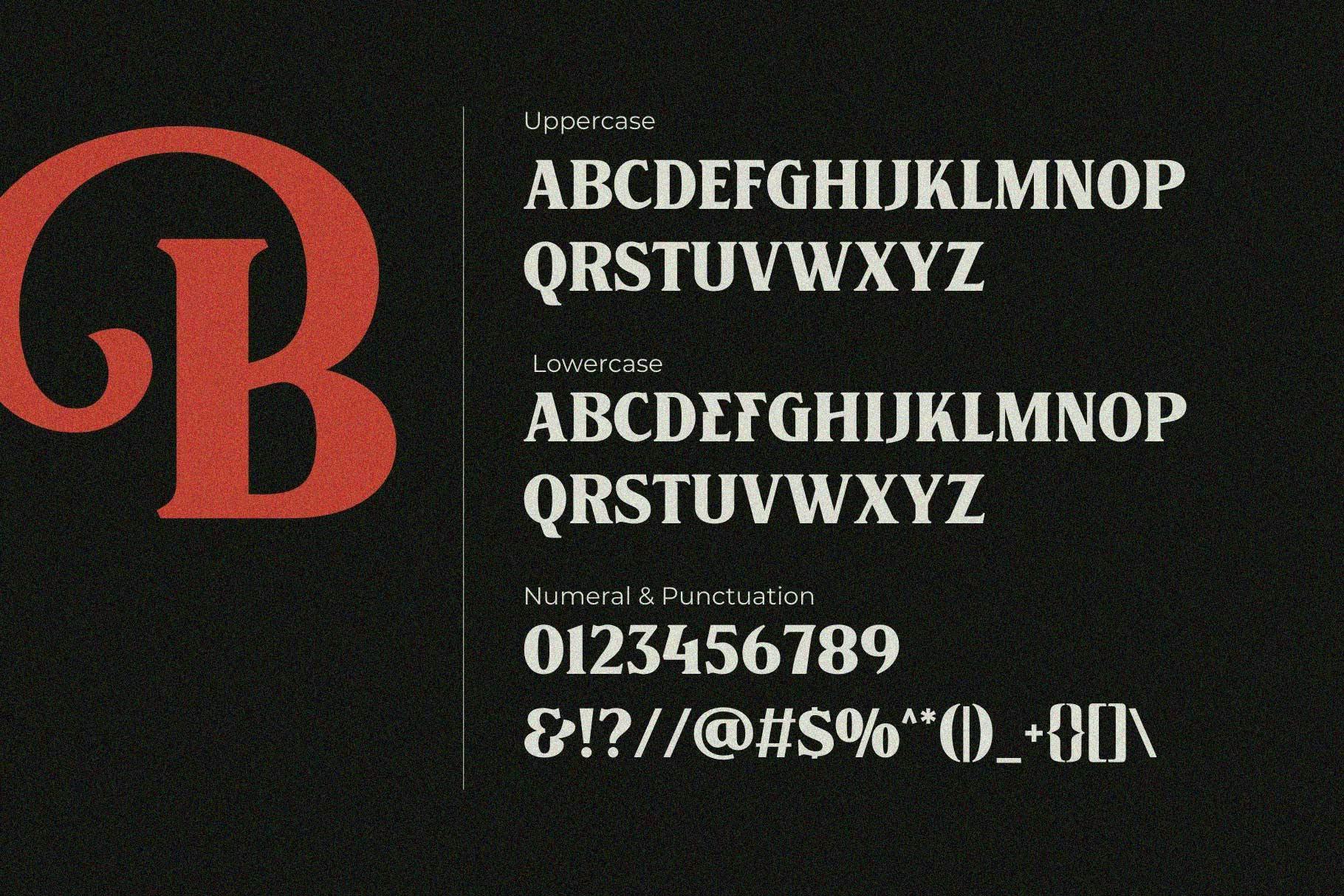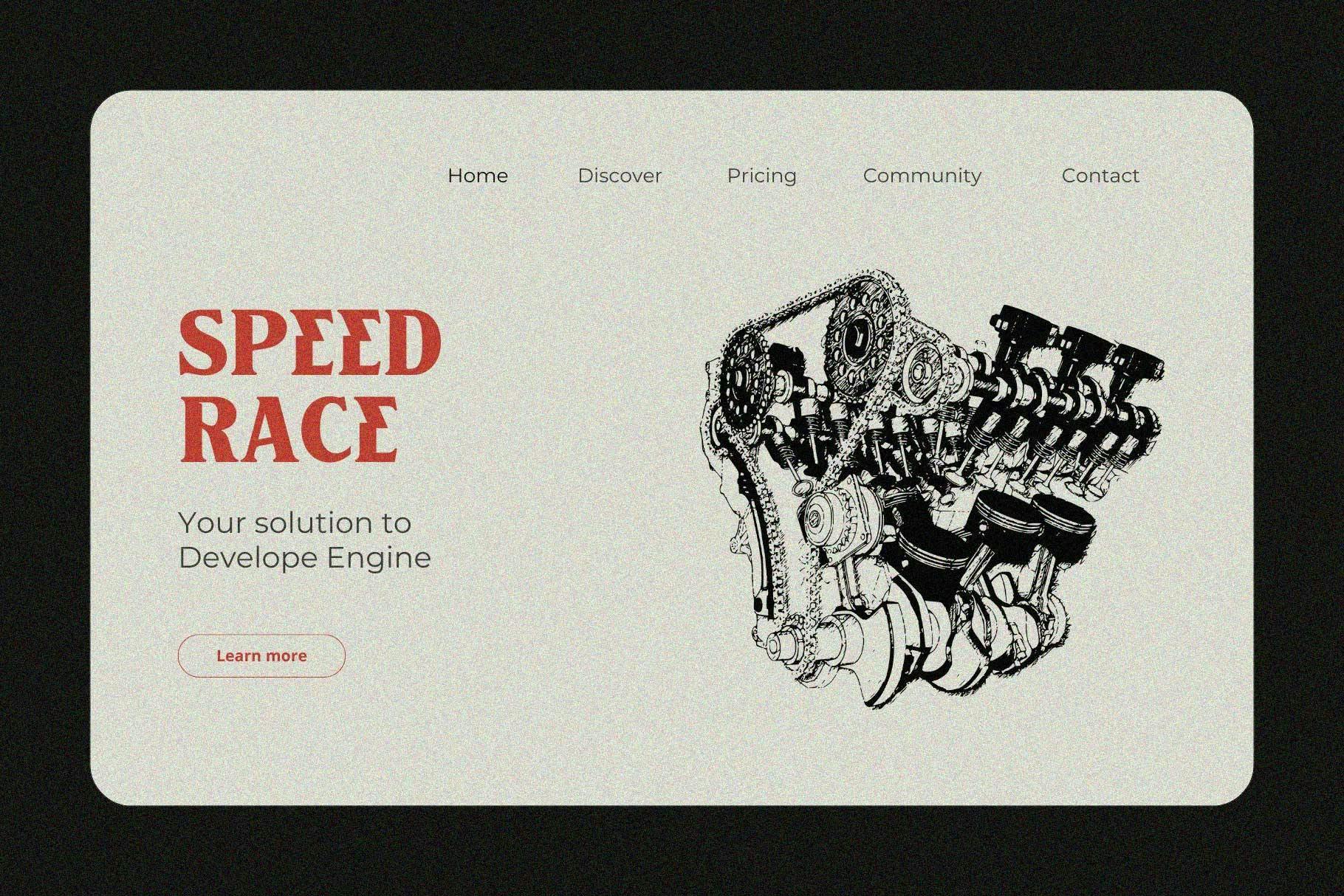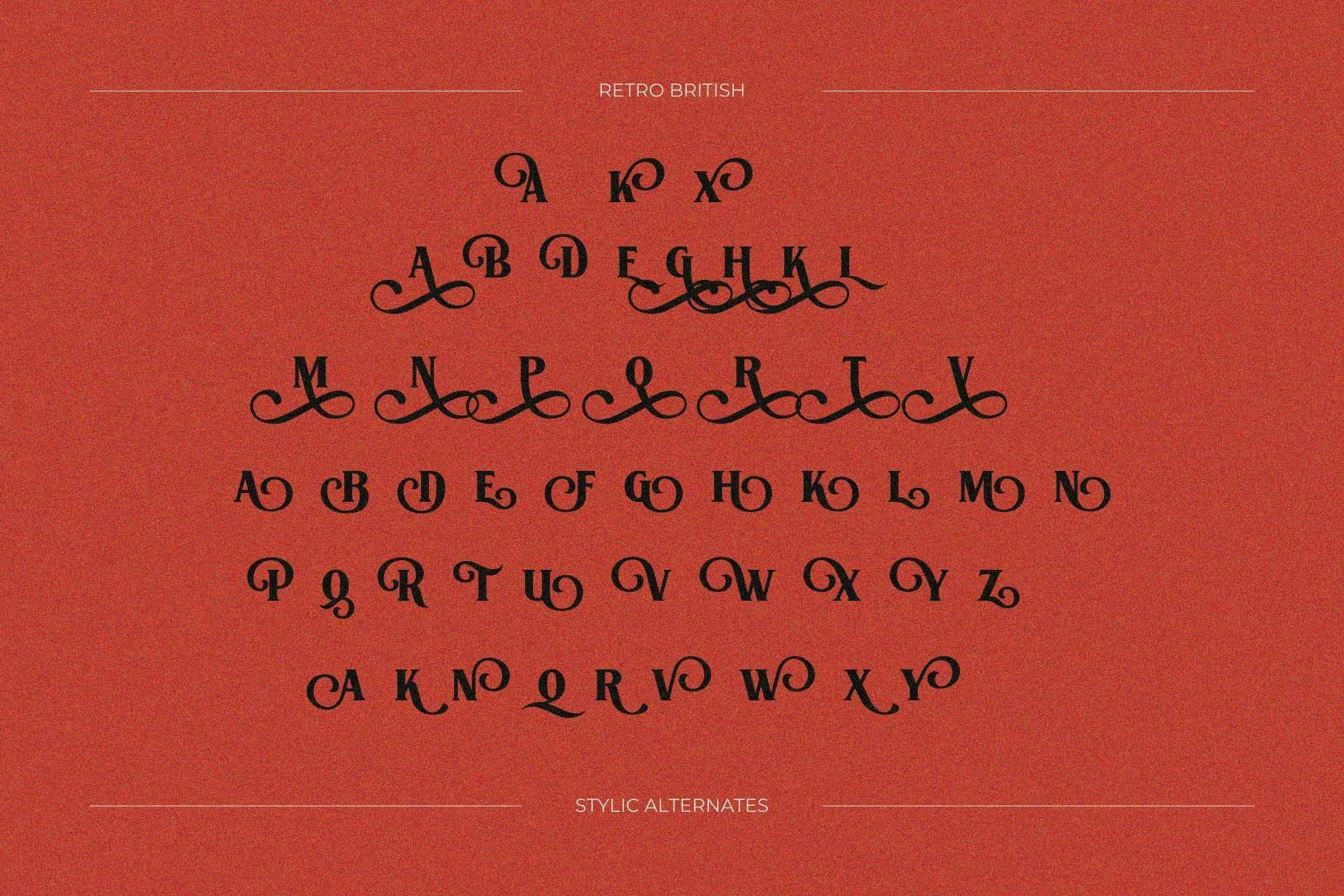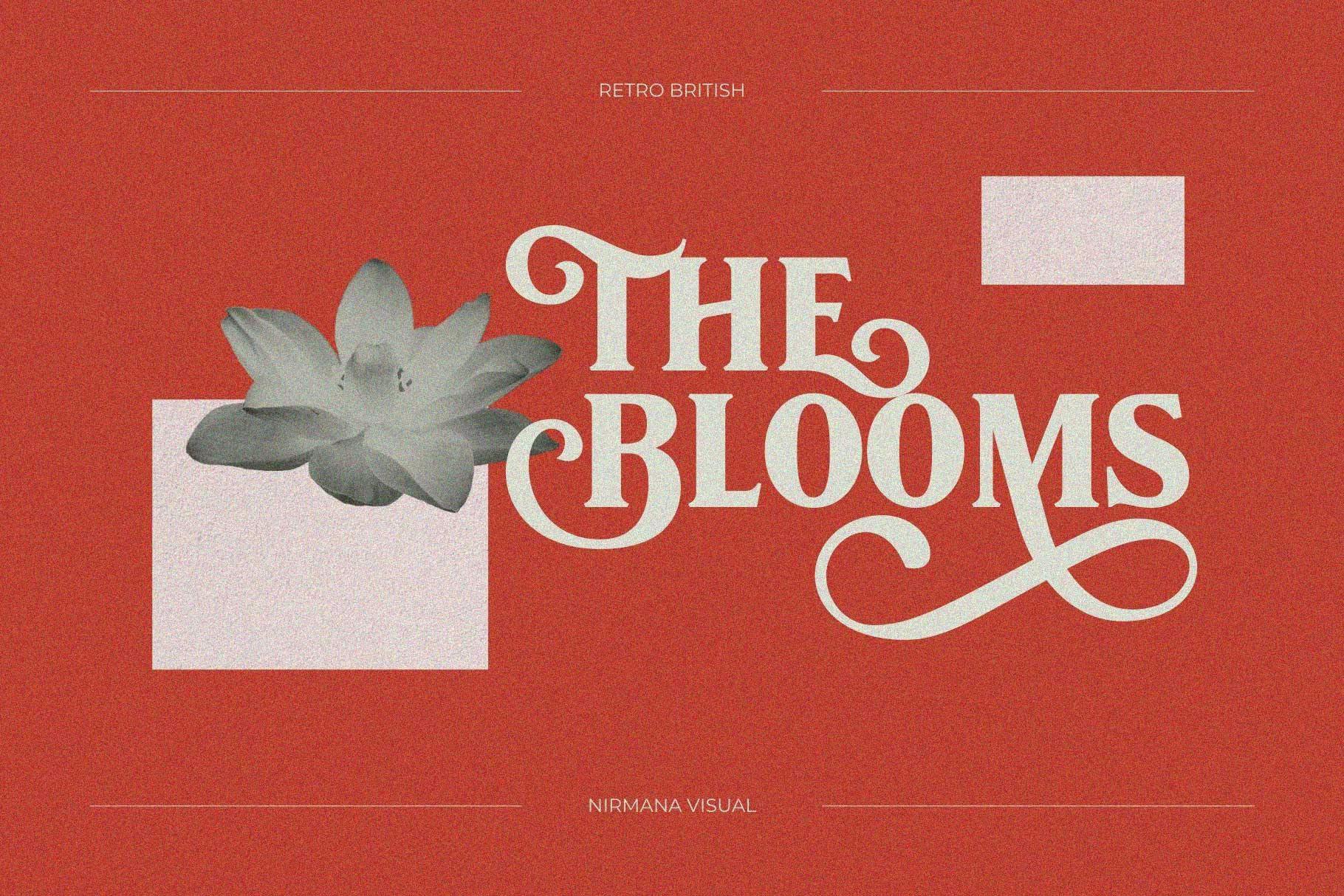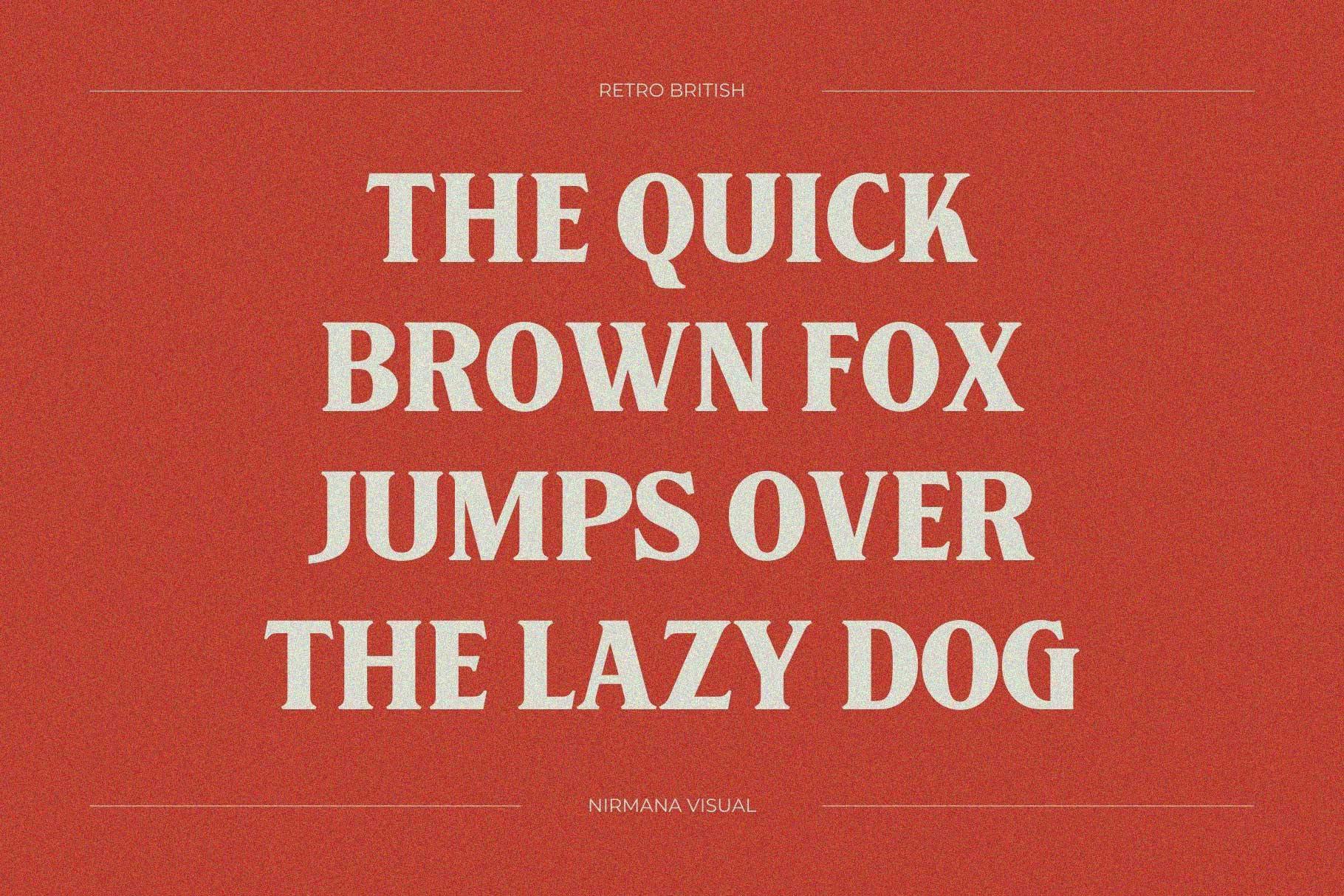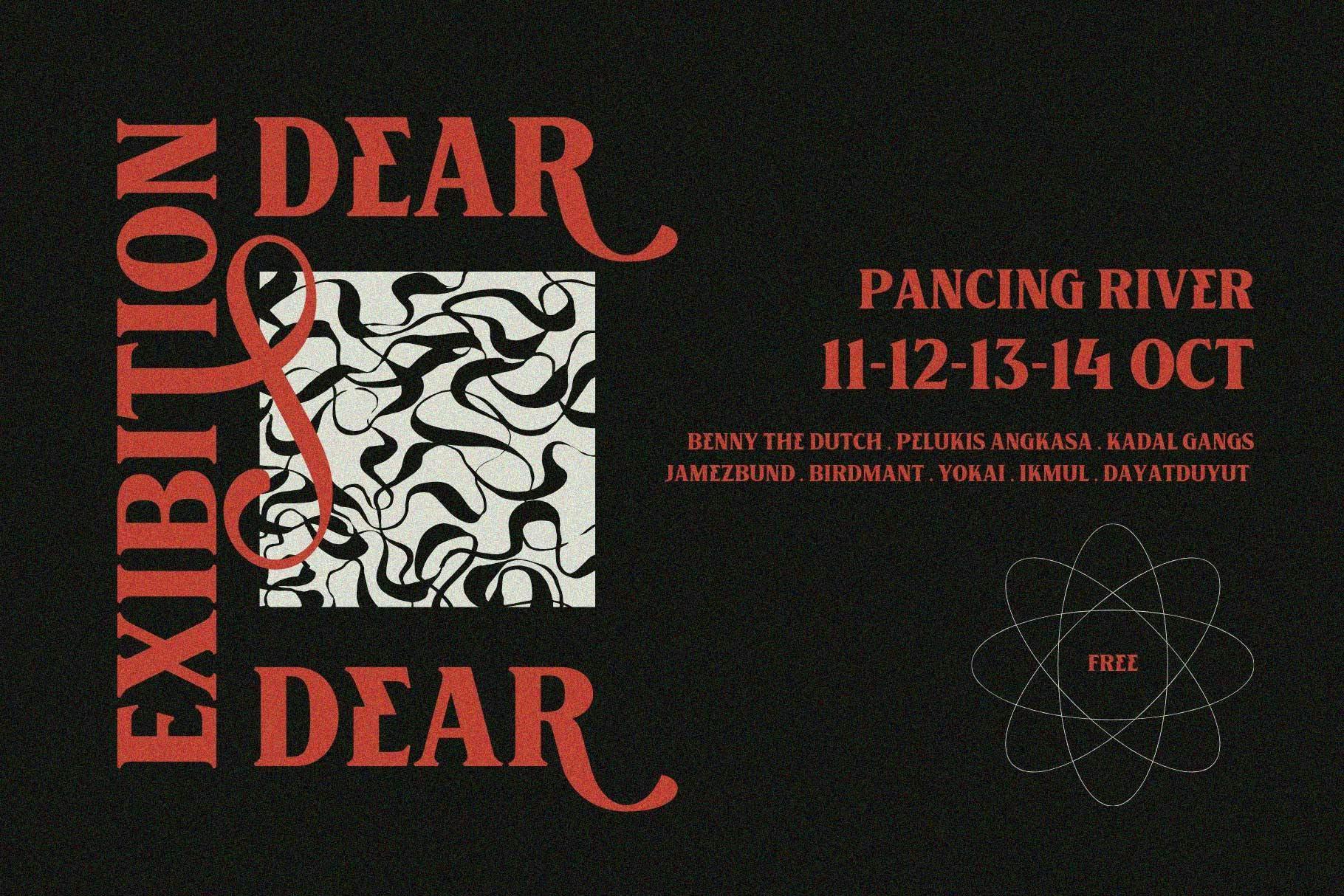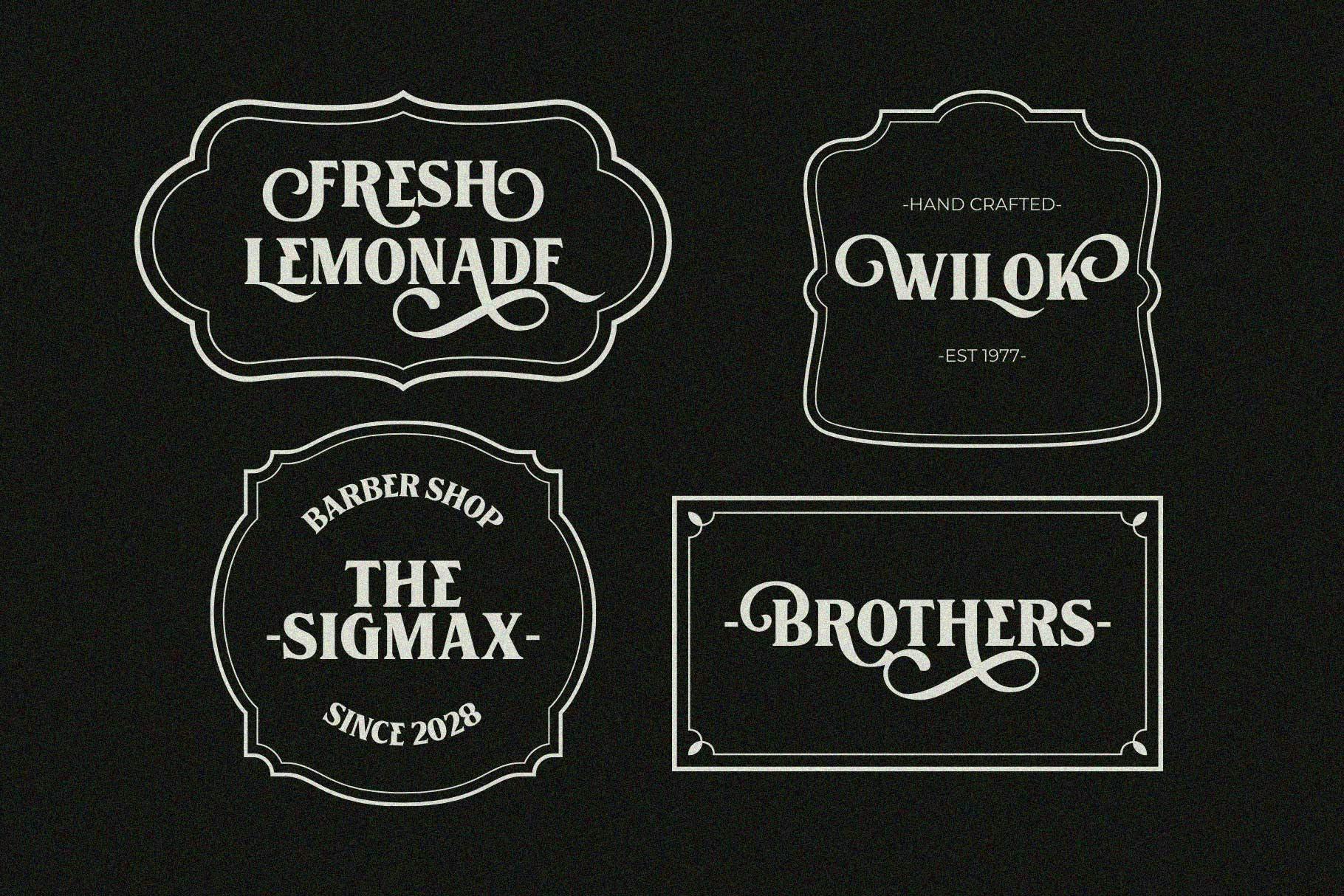
Retro British Logo Font
فونت رتیرو بریتیش، انتخابی عالی برای طراحی لوگو و پروژه‌های تبلیغاتی شما.
فونت لوگو رتیرو بریتیش - یک تایپ‌فیس سریف نمایشی.
فونت رتیرو بریتیش با زیبایی و هماهنگی تایپوگرافی، مناسب برای انواع پروژه‌های طراحی از جمله لوگو و برندینگ، پست‌های شبکه‌های اجتماعی، تبلیغات و طراحی محصولات است.